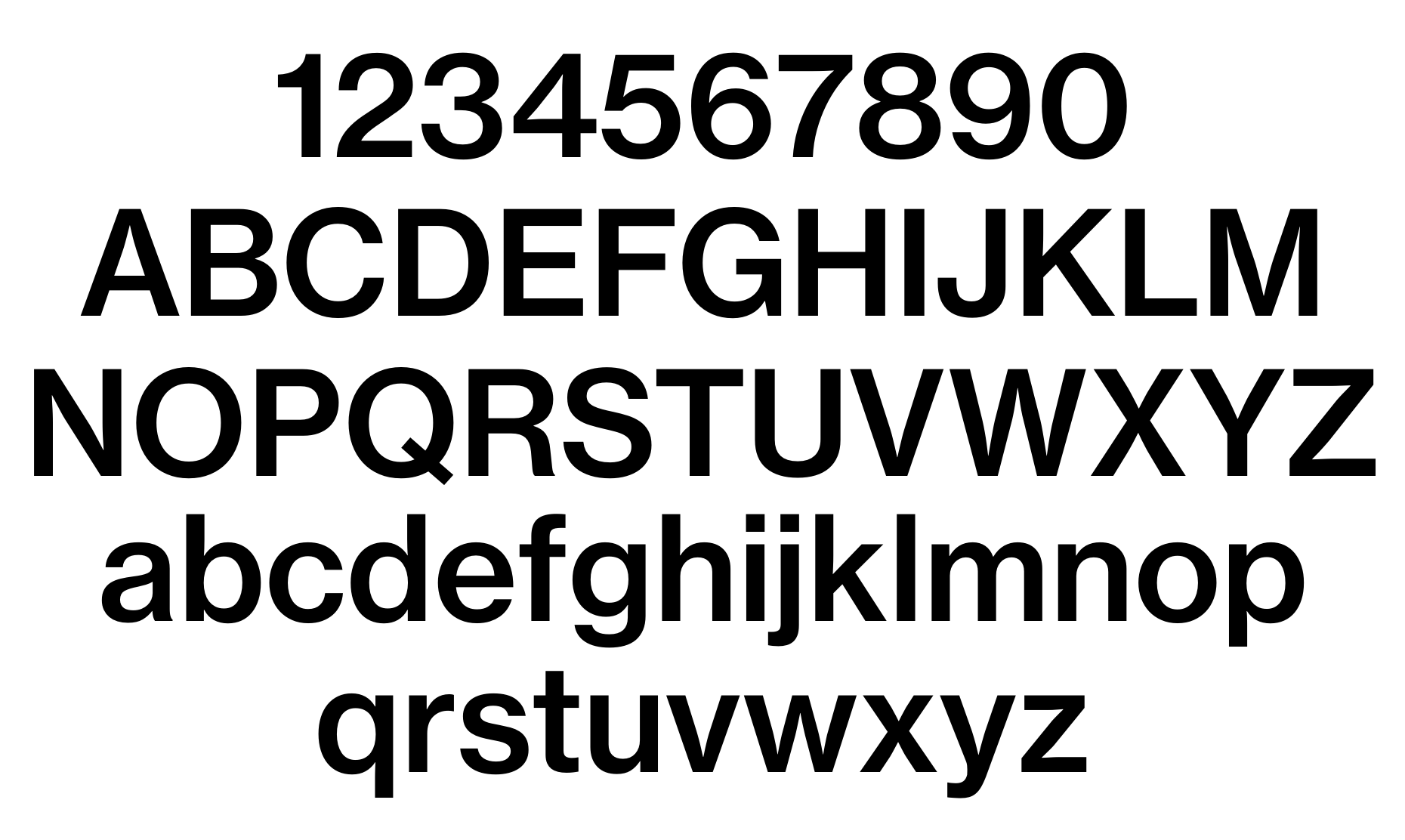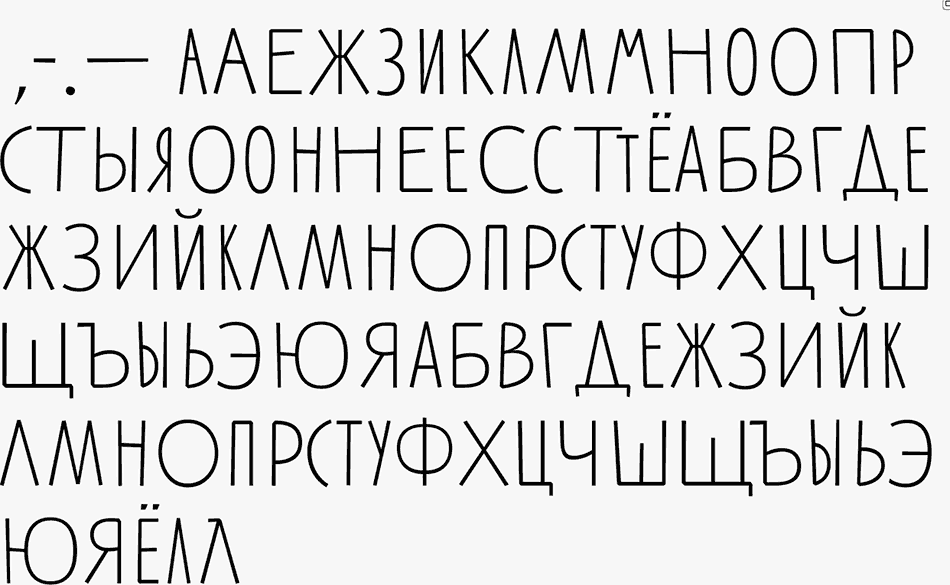
Гротески
Также называются рубленые шрифты, Grotesk (в Германии), Grotesque (в Англии и Франции), Gothic (в Америке). Впервые наборные шрифты без засечек появились в начале XIX века в Англии, хотя подобная форма знаков применялась еще в надписях античной Греции. Вначале применялись исключительно как акцидентные, но в ХХ веке стали использоваться для набора текста. Характеризуются, как правило, малой контрастностью или полным отсутствием визуального контраста между основными и соединительными штрихами. В соответствии с формой овалов, наличием или отсутствием контраста, степенью открытости знаков и степенью разноширинности гротески делятся на старые, новые, геометрические и гуманистические. Иногда к гуманистическим гротескам относят также так называемую ленточную антикву – умеренно контрастный шрифт без засечек, конструкция которого повторяет один из видов антиквы.
Старые гротески
Первый гротеск появился в 1816 году в Англии.
Новые гротески
Новые гротески развивают принципы построения старых гротесков. Они появились в 50-х годах ХХ века и были вызваны к жизни потребностями функциональной швейцарской школы типографики. Новые гротески гораздо изящнее своих предшественников и почти не имеют отличительных черт, что позволяет характеризовать эти шрифты как стандартные и незаметные. Это закрытые одноширинные шрифты почти без контраста, с крупным очком строчных знаков, сильно развитые по начертаниям. Верхние выносные элементы этих шрифтов равны росту прописных знаков. Как правило, в новых гротесках применяются наклонные начертания (не курсивные). Углы наклона знаков от среднего до значительного.
Открытые гротески
Самый новый и самый современный тип гротесков. Общая черта
для всех разновидностей таких гротесков — открытость и негеометричность форм. Кроме того, довольно многие из них обладают
небольшим контрастом; только в открытых гротесках встречаются
скошенные срезы вертикальных штрихов.
гротески — тип гротесков, наиболее близкий по форме к антикве (а имен-
но к гуманистической/ренессансной антикве). Появились они как реакция на чрезмерно геометризированную форму геометрических гротесков, в 30-х годах ХХ века в Англии появились гротески нового типа, форма, структура и пропорции которых непосредственно базировались на конструкции антиквы старого стиля. В последнее время эти гротески получили широкое распространение как самостоятельные гарнитуры, так и в составе супергарнитур, которые разрабатываются как системно связанные шрифты различных классификационных групп (например, антиква и гротеск).
Механистические гротески
Антиква-гротески
Акцидентные и текстовые шрифты, по форме промежуточные между гротеском и антиквой. Имеют на концах штрихов либо едва заметные утолщения, либо маленькие острые засечки.
Геометрические
Геометрические гротески принципиально строятся на основе простейших геометрических форм – окружности, квадрата, равностороннего треугольника. Эти шрифты появились в 30-е годы ХХ века в Германии под воздействием идей конструктивизма и школы дизайна Баухауз. Это, как правило, открытые неконтрастные разноширинные гротески. Очко строчных у ранних геометрических гротесков было не очень большим, близким по пропорциям к антикве старого стиля.
Однако во 2-й половине ХХ века были разработаны геометрические гротески с очень крупным очком строчных. У этих шрифтов только наклонные (не курсивные) начертания с небольшим углом наклона. Также к этой подгруппе можно отнести акцидентные гротески с овалами, близкими по форме к квадрату и прямоугольнику.
Моноширинные
Специальные шрифты, все знаки которых имеют одну и ту же толщину (ширину). Применяются для набора таблиц, листинга программ и в других случаях, когда требуется полное совпадение колонок и знаков по вертикали набора.
Руководство по распознаванию стилей шрифтов
Научиться различать стили шрифтов, было одной из самых сложных задач, когда я только начинал работать дизайнером. Будучи самоучкой, единственное существенное отличие, которое я видел, было то, что шрифт был либо с засечками (serif), либо без них (sans serif). Но чем больше я изучал, тем больше понимал, насколько широка вселенная стилей шрифтов.
Это руководство является выдержкой из главы 3 из книги «Лучшая веб-типография для лучшей сети», автор Matej Latin.
Книга состоит из 13 глав, в которых читатель разрабатывает и создает пример веб-сайта.
Теперь я знаю, почему так сложно распознать стиль шрифта. Когда дело доходит до типографики, особенно если речь идет о шрифтах, все дело в деталях. Трудно даже представить, сколько работы уходит на разработку шрифта и сколько дизайнеров вкладывают свой труд в мельчайшие детали, которые остаются незаметными для большинства людей. Таким образом, чтобы найти ключевые моменты, позволяющие различать стили шрифтов, нам нужно научиться видеть эти детали. Но для начала, для чего вам нужно распознавать стили шрифтов? Почему бы просто не выбрать и не комбинировать шрифты, основываясь на внутреннем чувстве стиля и эстетики?
Ну, вы можете так и поступить. На самом деле я так делал долгое время, особенно в начале моей карьеры.
Но у меня была огромная проблема. Я никогда не был уверен в своих решениях при выборе шрифта, и что разработанная мной комбинация шрифтов хорошо взаимодействует между собой. Конечно, вы можете копировать другие или использовать самые популярные шрифты, основываясь на таких классификациях, как Top 10 самых популярных гарнитур Typewolf в 2019 году. Но не приводит ли это к чрезмерному использованию шрифтов? Посмотрите, что случилось с Helvetica, Gotham и Futura. Это те шрифты, которые используются так часто, что вы можете увидеть их буквально везде. Когда так происходит, они теряют свою уникальность. Использование очень популярного шрифта – это достоверный выбор, но при этом вы утратите свою оригинальность. Что касается качества, хотите ли вы, чтобы ваша типографика выделялась или гармонировала?
Открытые гротески
Самый новый и самый современный тип гротесков. Общая черта
для всех разновидностей таких гротесков — открытость и негеометричность форм. Кроме того, довольно многие из них обладают
небольшим контрастом; только в открытых гротесках встречаются
скошенные срезы вертикальных штрихов.
Разновидностью открытых гротесков являются гуманистические
гротески — тип гротесков, наиболее близкий по форме к антикве (а имен-